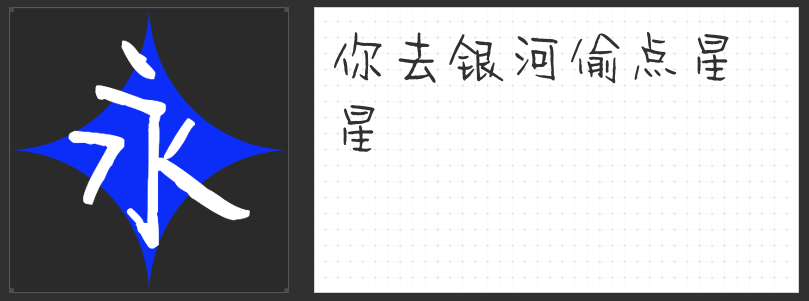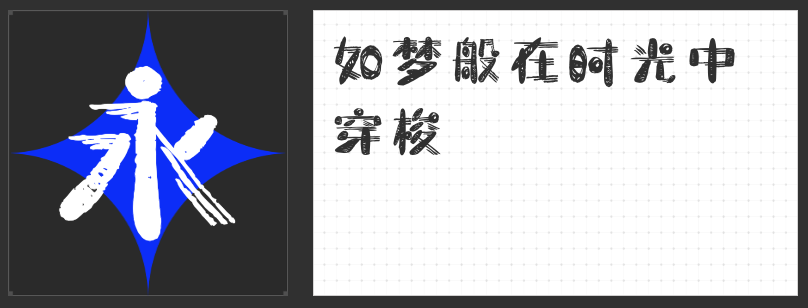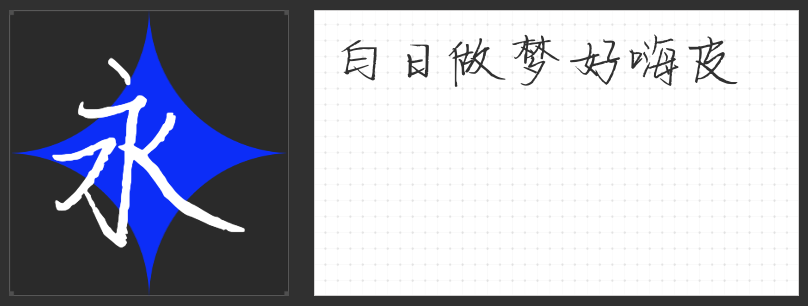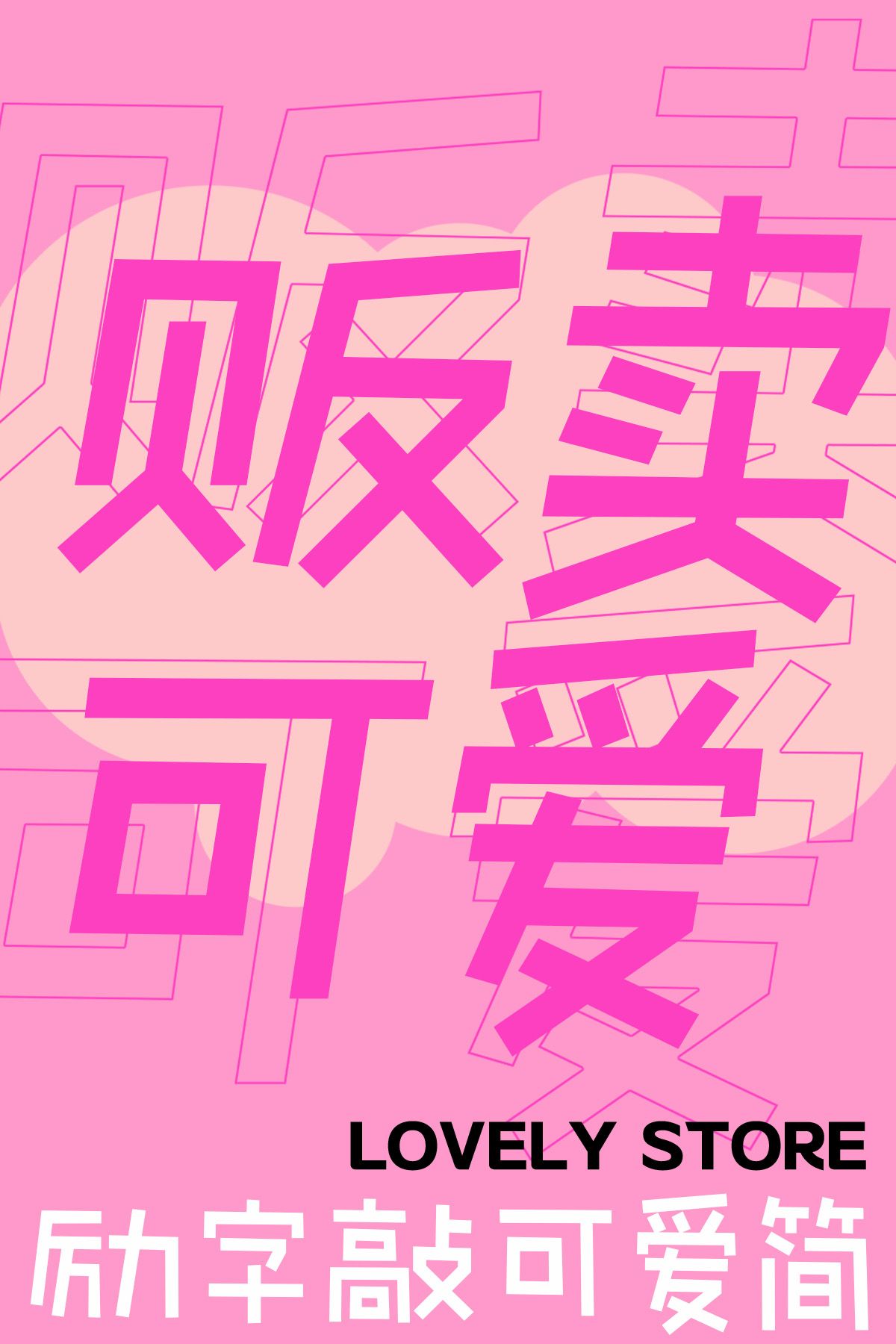
让你的文字也“萌”起来:INS风清新可爱手写字体推荐
在这个追求个性与美感并存的时代,INS风以其清新脱俗、简约而不失温馨的特点,赢得了无数年轻人的喜爱。而手写字体,作为传递情感与个性的独特方式,与INS风相结合,更是碰撞出了不一样的火花。今天,就为大家推荐几款INS风清新可爱的手写字字体,让你的文字也“萌”起来!
励字敲可爱简 常规
励字敲可爱简 常规,从名字上就透露出一种激励人心又不失童趣的气息。它的字形设计简约而不失精致,每一笔一划都仿佛是精心雕琢的艺术品,既保留了手写体的自然与随性,又加入了现代设计的简约元素,使得整体看起来既清新又可爱。
无论是用于社交媒体的配图文案,还是手账日记的记录,亦或是温馨浪漫的贺卡制作,励字敲可爱简 常规都能轻松驾驭,为作品增添一抹不可多得的可爱气息。
云书法恋爱偷着乐简
云书法恋爱偷着乐简,这款字体的名字就仿佛一首浪漫的情诗,让人不禁遐想联翩。它巧妙地将传统书法的行云流水与现代设计的简约明快相结合,创造出一种既古典又清新的独特风格。字体中的每一笔一划,都仿佛是在云端漫步,轻盈而自由,带着一丝丝恋爱的甜蜜与偷乐的俏皮。将云书法恋爱偷着乐简用于社交媒体上的心情分享、手账日记中的情感记录都是很好的选择。
MyFont凌渡未卜简
MyFont凌渡未卜简,名字就蕴含着一种探索未知、追求自由的精神。其字形设计简约而不失精致,每一笔一划都透露出一种随性而不羁的气息,仿佛是在告诉我们:生活就像一场未知的旅行,充满了无限可能与惊喜。
它的线条流畅而富有变化,既保留了手写体的自然韵味,又融入了现代设计的简约美感。MyFont凌渡未卜简无论是用于社交媒体上的个性签名,还是手账日记中的温馨记录,亦或是创意海报的标题设计,这款字体都能以其独特的风格,吸引众人的目光。
字恋狂白日梦简
字恋狂白日梦简,这款字体的名字就仿佛是一首未完的诗,引人遐想。它融合了手写体的自由与随性,同时又不失简约设计的精致感,让人一眼就能感受到那份来自白日梦的清新与梦幻。字体中的每一笔一划,都像是精心编织的梦境片段,既真实又虚幻,引领我们进入一个充满无限想象的空间。
无论是用于漫画中,还是绘本装帧,亦或是创意设计的文字元素,字恋狂白日梦简都能以其独特的清新可爱风格,为作品增添一抹不可多得的亮点。字恋狂白日梦简线条柔和而富有变化,既展现了手写体的自然美感,又融入了现代设计的时尚元素。
以上推荐的几款INS风清新可爱手写字体,每一款都有其独特的魅力与风格。它们不仅能够丰富你的文字表达,更能让你的作品在众多信息中脱颖而出,成为一道亮丽的风景线。不妨试试看,用这些可爱的字体,为你的生活增添一抹不同的色彩吧!